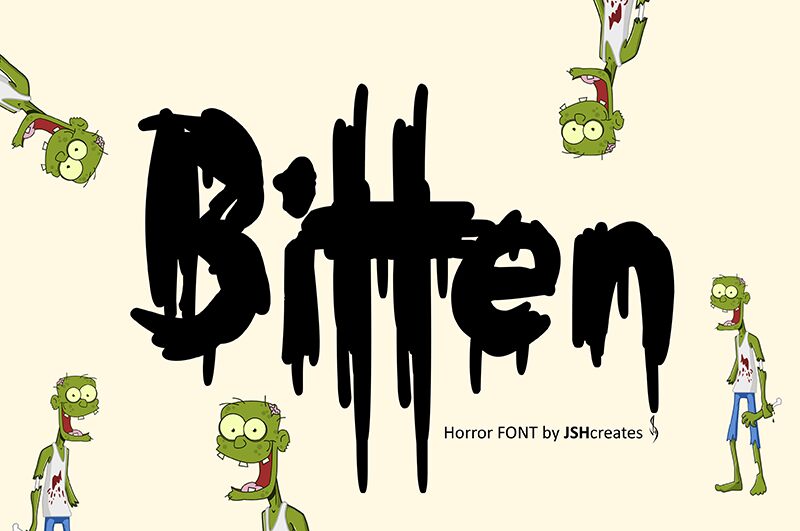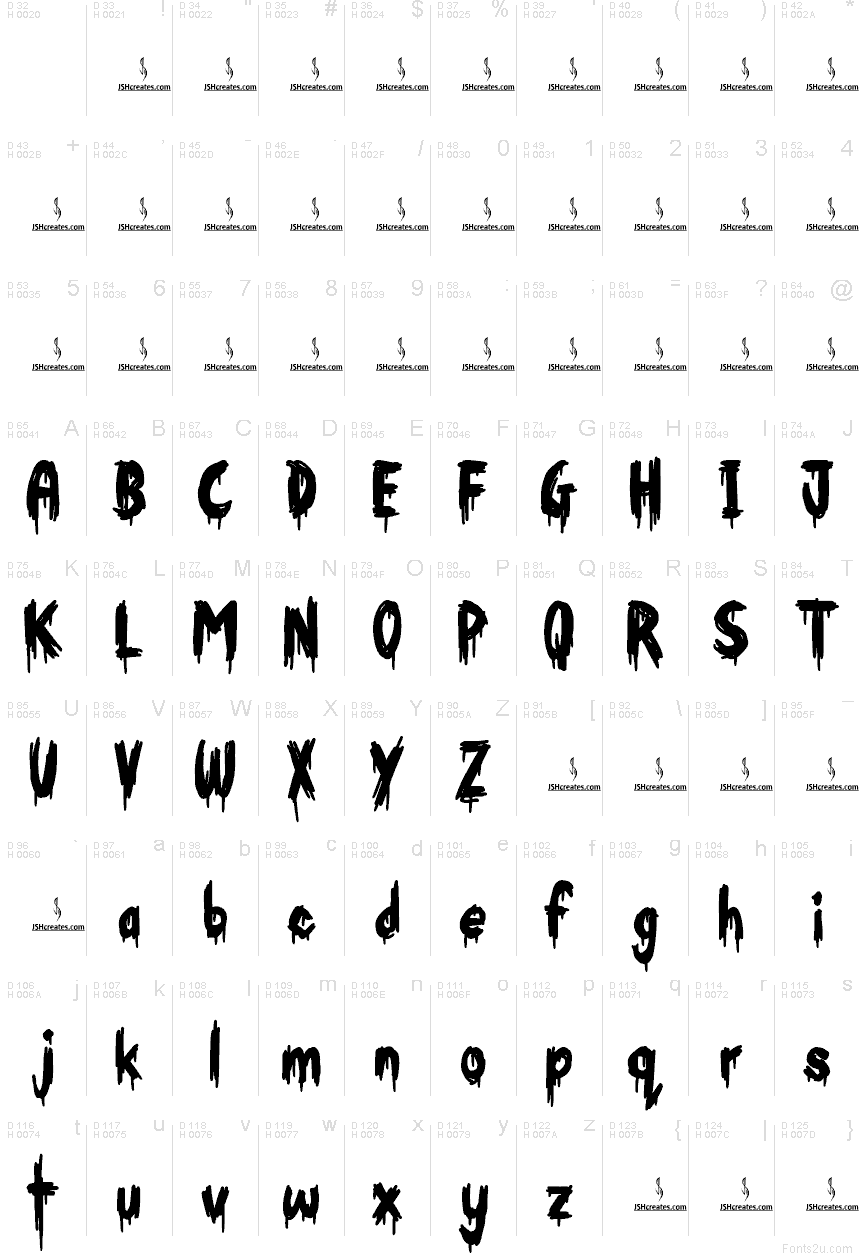
Bitten by Bitten © — это бесплатный декоративный шрифт в стиле хоррор с эффектом размазанной краски. Буквы выглядят так, будто их выцарапали на бумаге: с толстыми кляксами, рваными краями и длинными подтеками, которые повторяются во всем наборе. Это придает шрифту «сырой», свежий вид, в противовес аккуратному и выверенному дизайну.
Он идеально впишется в постеры фильмов ужасов, флаеры для Хэллоуина, айдентику аттракционов страха, заставки инди-игр и мрачные заголовки, где нужно сделать короткое слово неряшливым и пугающим. Поскольку шрифт бесплатный, он также отлично подходит для титров и быстрой графики в соцсетях: стекающие штрихи создают необходимую атмосферу сами по себе.